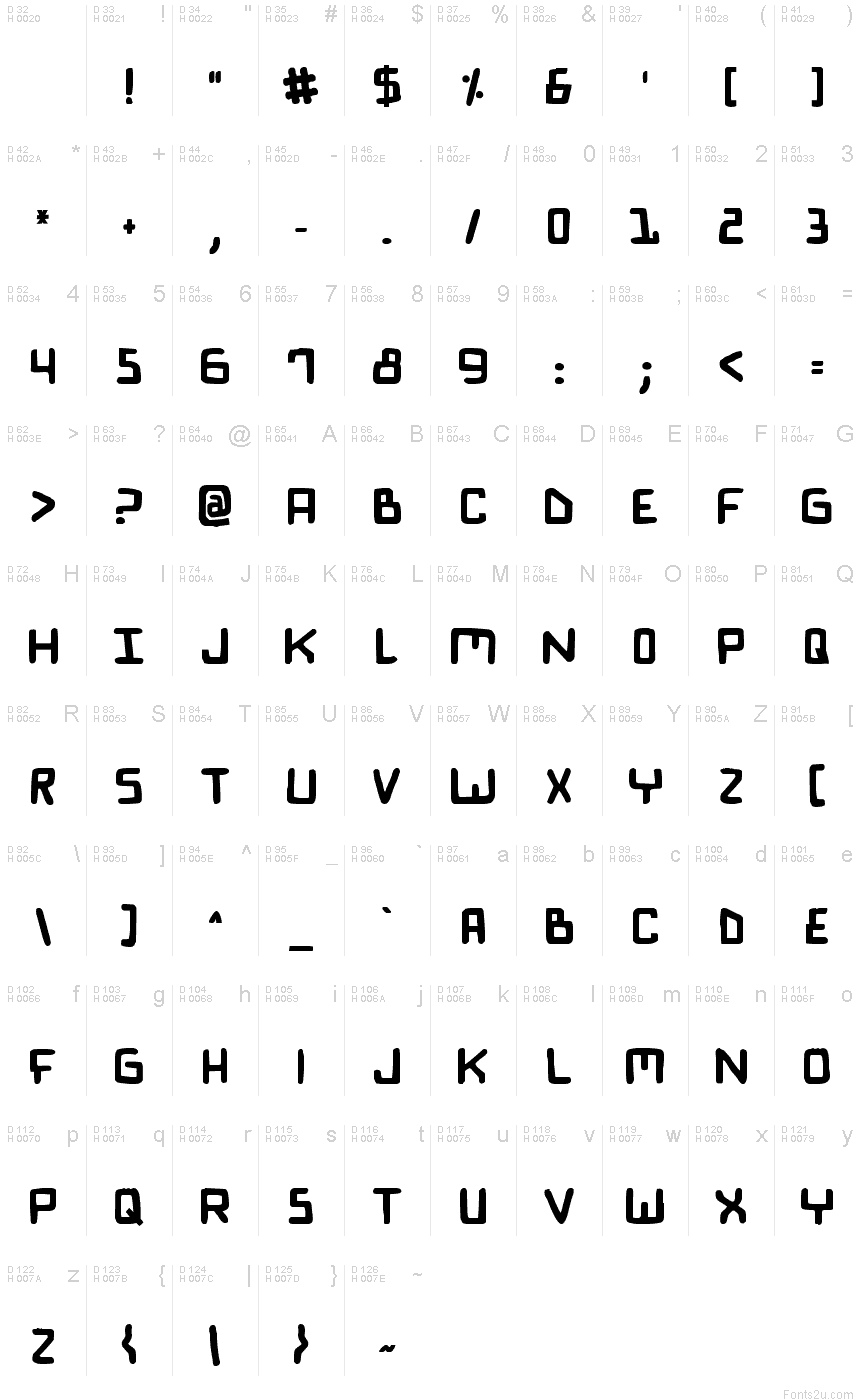
Náhled písma Bionic Comic Bold
Bionic Comic Bold od Daniela Zadoroznyho z Iconian Fonts je bezplatné komiksové display písmo, které vypadá, jako by vypadlo přímo ze sci-fi komiksu. Vysoká, tubulární písmena s hranatými rohy a úzkými vnitřky mu dodávají technický nádech – něco mezi sobotním superhrdinou a futuristickým rozhraním. Díky své tučné váze a pevné struktuře každé slovo okamžitě vynikne jako komiksový zvukový efekt.
S Bionic Comic Bold získají vaše nadpisy a loga hravý, a přitom energický náboj. Tento bezplatný font se skvěle hodí na obálky komiksů, dětské hry, náhledy na YouTube, sci-fi plakáty, obaly hraček nebo tvorbu postav. Vynikne zejména ve velkých velikostech, kde mohou jeho robustní tvary pořádně vyniknout; pro hlavní text jej zkombinujte s čistým, neutrálním bezpatkovým písmem, aby rodina Bionic Comic mohla skutečně zazářit.